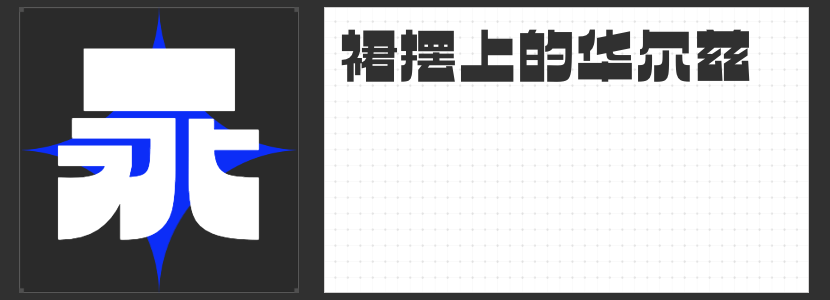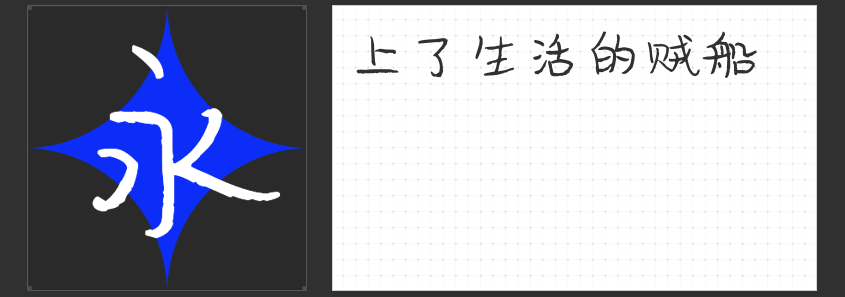
醒图合作精选:四款热门字体推荐
在创意无界的数字时代,醒图作为视觉创意的先锋平台,携手励字造梦共创字库,精心挑选四款用于醒图app内特色鲜明、风格迥异的字体,为设计师与爱好者们开启了一场视觉盛宴。这不仅是字体的选择,更是灵感与梦想的碰撞。
首推“MyFont凌渡猪猪简”,以其圆润可爱的形态,仿佛每一笔都跳跃着童真与欢乐。这款字体适用于卡通插画、儿童绘本及温馨场景设计,轻松营造出温馨和谐的氛围,让作品瞬间萌力四射。
紧接着是“励字憨憨简”,以其憨态可掬的笔触,展现了独特的亲和力与趣味性。无论是社交媒体文案还是广告海报,都能以它独有的魅力吸引眼球,让信息传递更加生动有趣,是拉近品牌与消费者距离的绝佳选择。
“造字侠陈坤风行简繁”则融合了现代与传统,既有简约时尚的线条,又不失繁体字的韵味与深度。这款字体适合高端品牌宣传、文艺作品标题等场景,能够彰显出作品的文化底蕴与时尚气息,让每一次呈现都成为经典。
最后,不得不提的是“励字逆反差圆舞简 超级黑”,它以其极致的反差与强烈的视觉冲击力,成为了个性表达与创意突破的代名词。超级黑的厚重与圆舞简的柔美相结合,创造出一种前所未有的视觉体验,非常适合用于摇滚乐、极限运动或科技产品的宣传设计,让每一份创意都充满力量与激情。
四款字体,四种风格,励字造梦与醒图的此次合作,不仅丰富了设计素材库,更为每一位创作者提供了无限的想象空间和表达可能。让我们携手并进,在字体的海洋里遨游,共同创造更多令人瞩目的视觉奇迹。